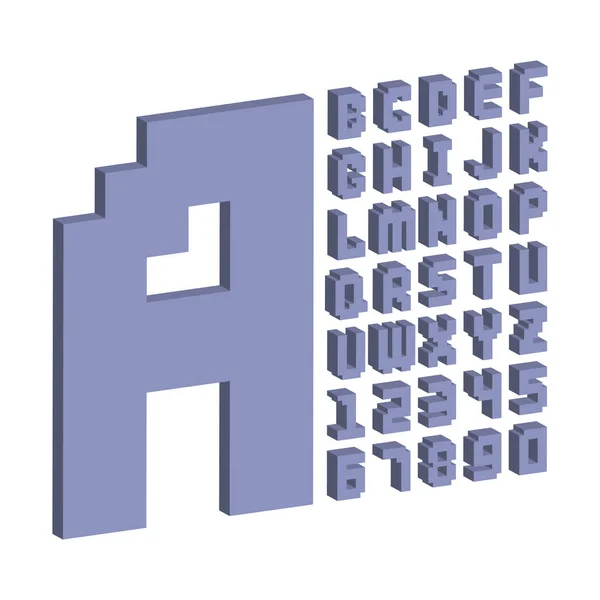
Bleo
Шрифт Bleo является одним из креативных дизайнов дизайнера MrtheNoronha. Этот шрифт разработан как цветочный, то есть такие символы, как буквы C, J и L в конце, круглые и цветочные, поэтому вы можете использовать его для дизайна видеоигр для девочек, например, косметика, мода или даже игрушки для девочек.
I pixel u
I pixel u Шрифт: демонстрирует ретро и геометрический стиль.